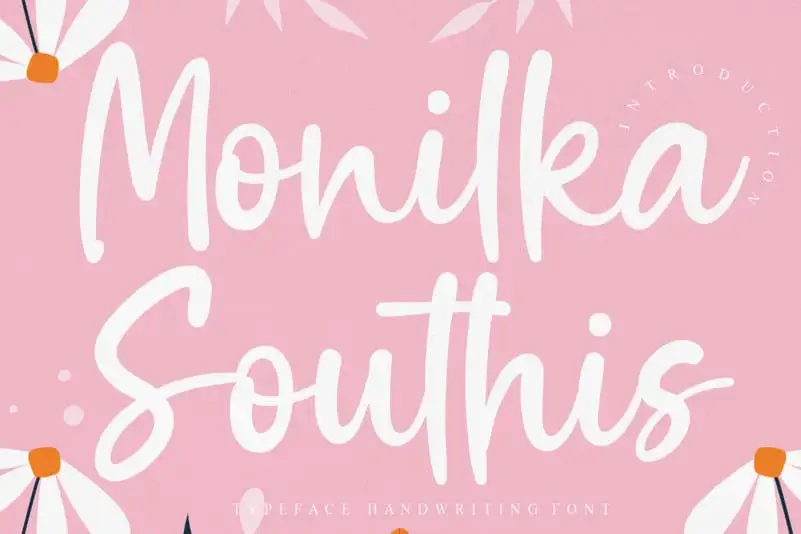
Monilka Southis Script Font – Fonte Grátis
Monilka Southis Script Font
Descubra Monilka Southis Script Font, uma elegante fonte escrita a mão que combina com perfeição os elementos artísticos do design. Especialmente projetada para aqueles que valorizam uma experiência única e criativa no layout de sua próxima peça de trabalho, esta fonte traz um toque pessoal às suas publicações digitais. Monilka Southis Script é mais do que uma simples ferramenta de escrita digital; ela transforma qualquer texto em uma verdadeira obra de arte. Seu traço fluido e característica tipográfica proporcionam um acabamento distintivo, fazendo da fonte um elemento crucial no seu design. Perfeita para editoriais, sites personalizados ou projetos onde o detalhe conta. Este é mais do que uma ferramenta de escrita; ele se torna a cara do seu trabalho. Monilka Southis Script é uma escolha inteligente para quem busca algo único e especial em suas fontes. Seja você um designer gráfico, web designer ou editor de conteúdo, este fonte vai dar sua marca pessoal às páginas que criou.